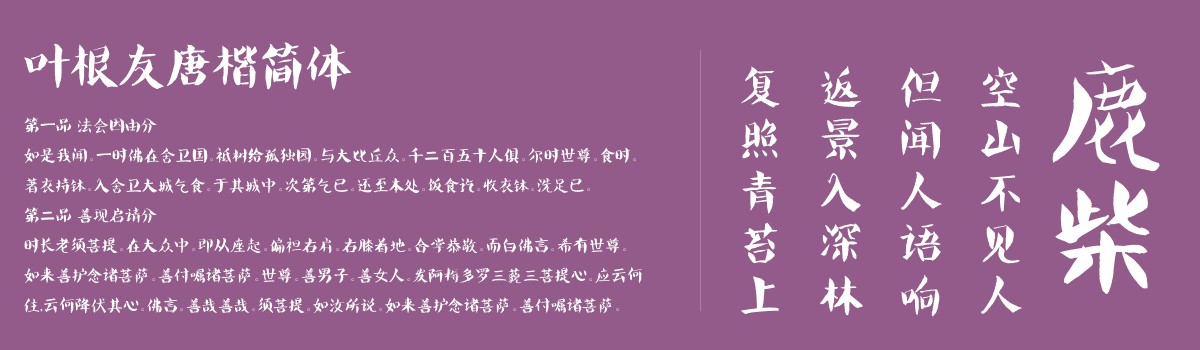
叶根友唐楷简体
字体介绍
叶根友唐楷是特楷字体的姊妹篇字体,在2014年3月开发完毕,整个字型较之前的特楷更加严谨,风格遒劲,自然而不失洒脱,是一款标题用字不错的选择。
叶根友的书法有着与众不同的风格体现,其行草书法是属于主要的书法表现形式,在取他之长、补己之短的精神努力追求下,取得许多叶根友书法爱好者的一致认同。叶根友说,书法艺术讲究的是不变中求变,行笔过程快中有慢,慢中有劲,动静结合、快慢相融、做到章法错落有致,书法布局空间的形式美等的书法创作理念。
叶根友唐楷书法是叶根友先生独创的一种楷书书法艺术表现形式,叶根友说:“传统书法和唐楷的书法艺术表现是完全不一样的,唐楷书法作品中的笔画运笔形式与传统书法作品有点背道而驰,点和竖的起笔运笔都非常的有突破性的表现力。主要体现在快、齐、力、虚、实、动、悠等表现特点。